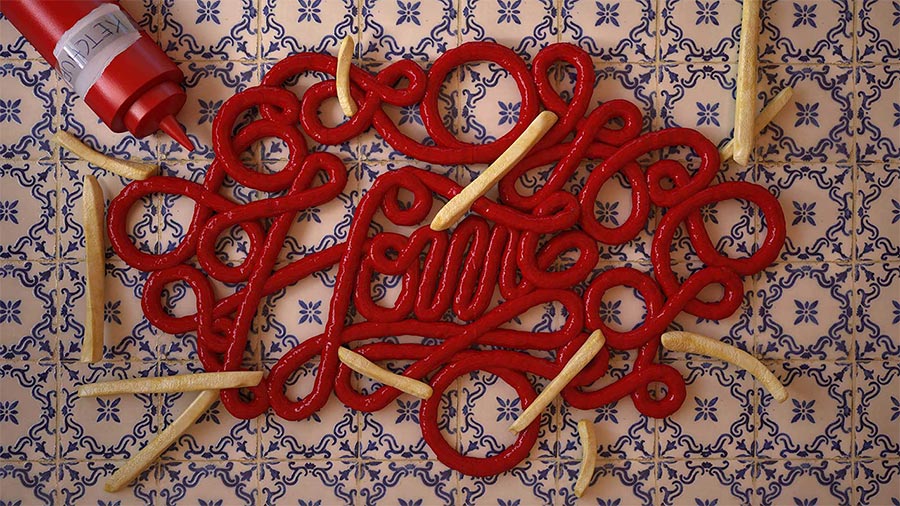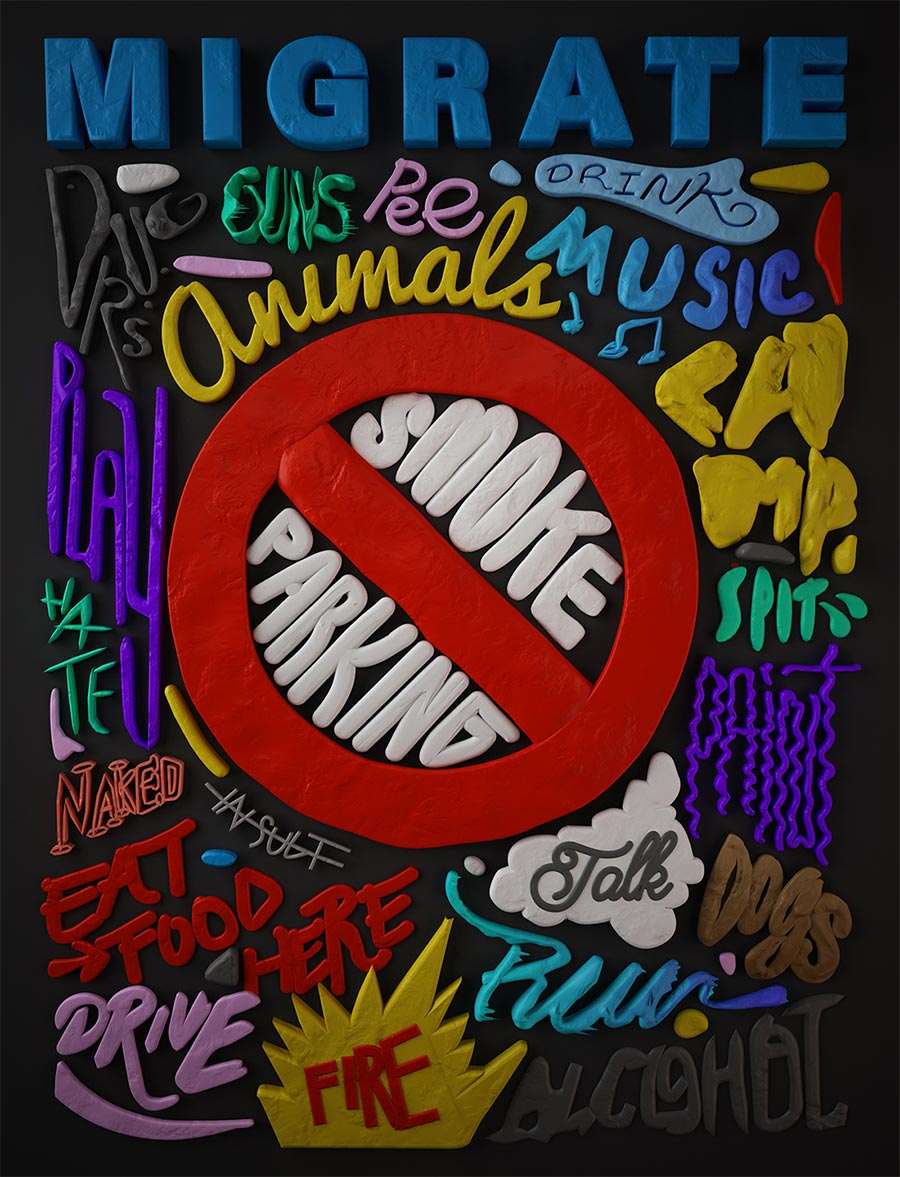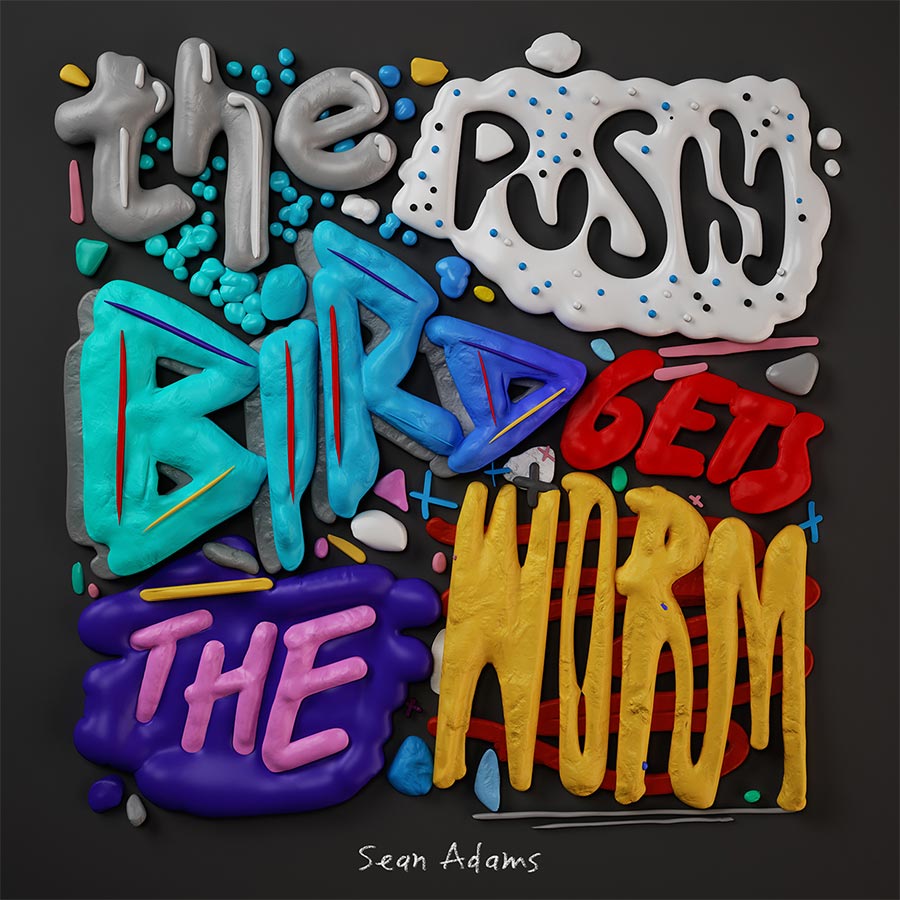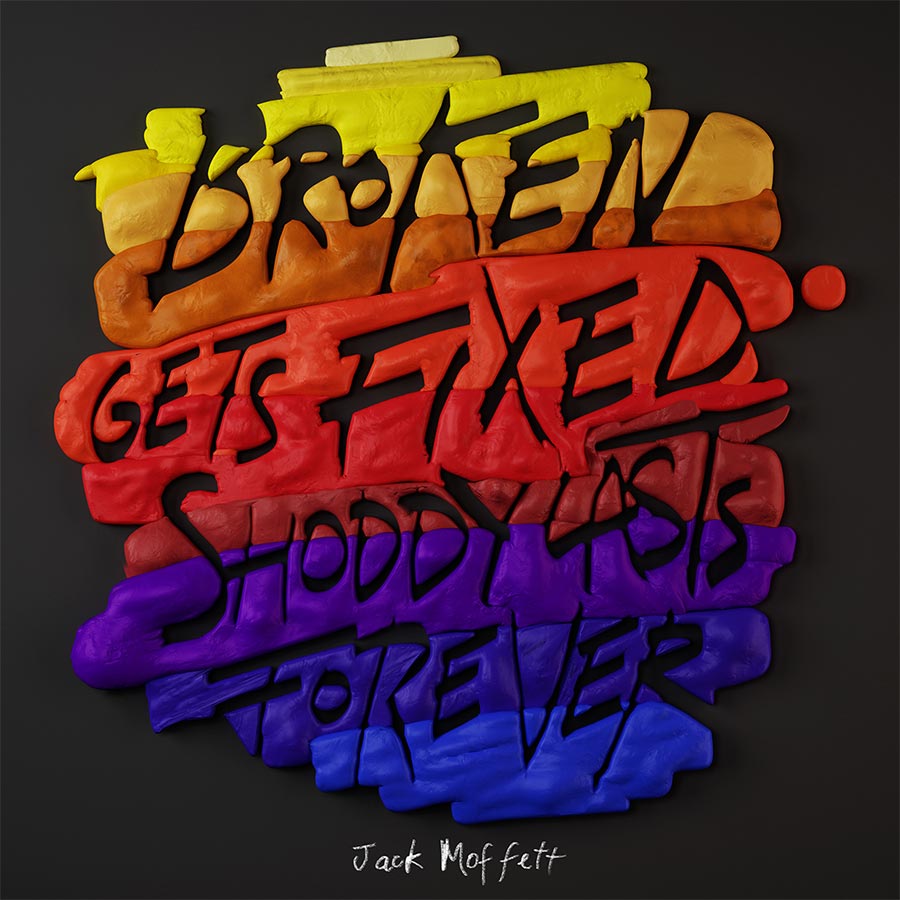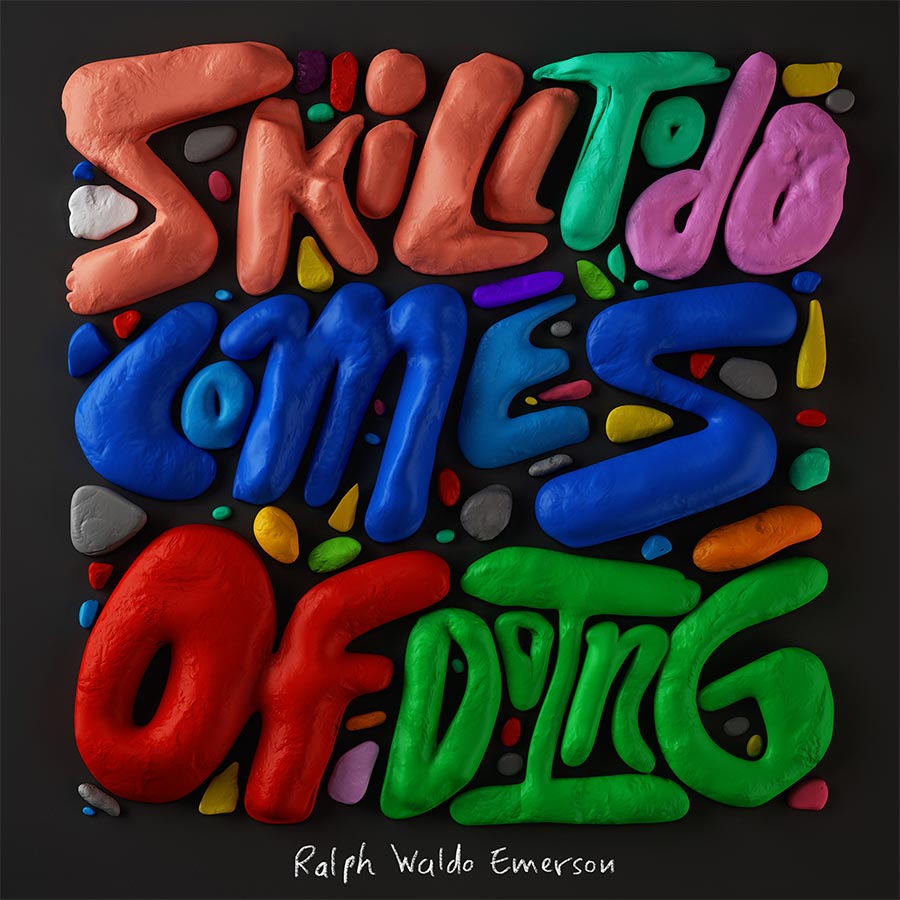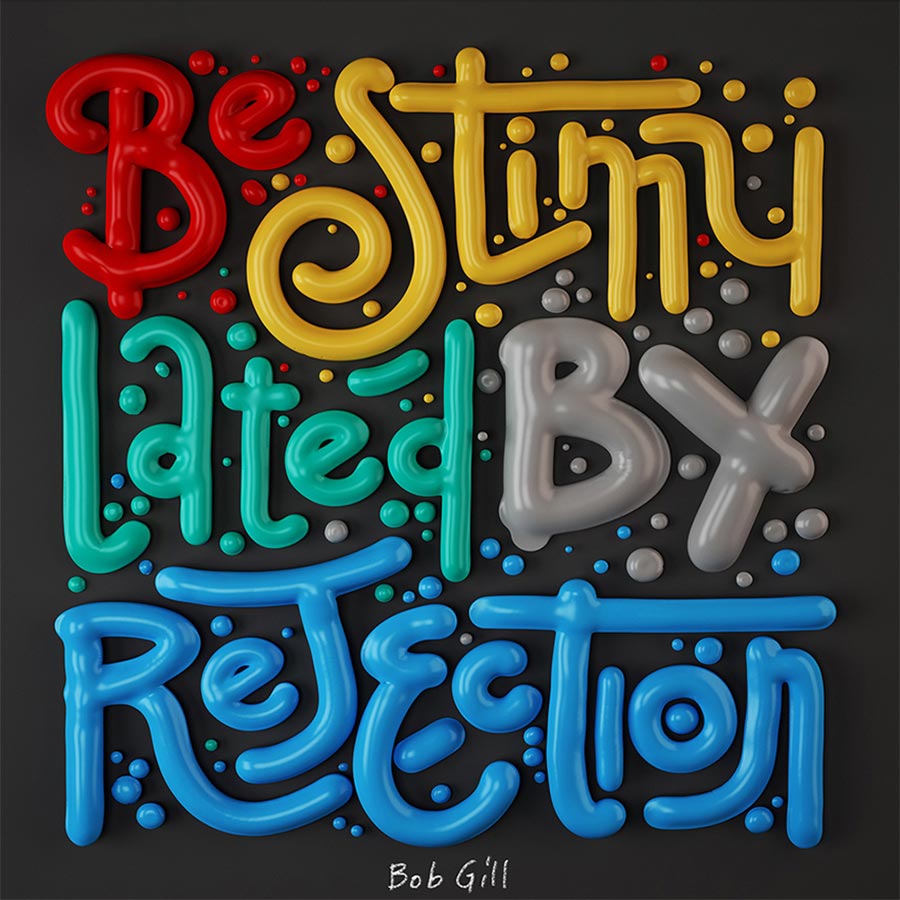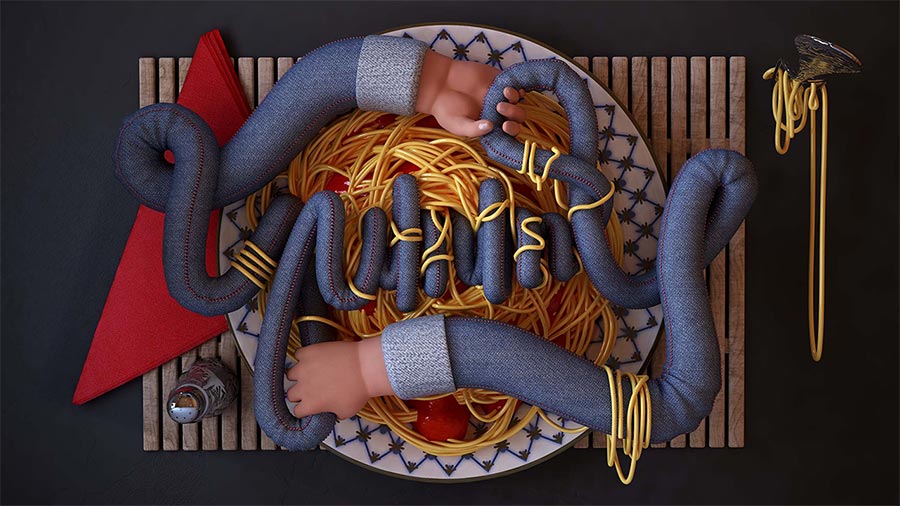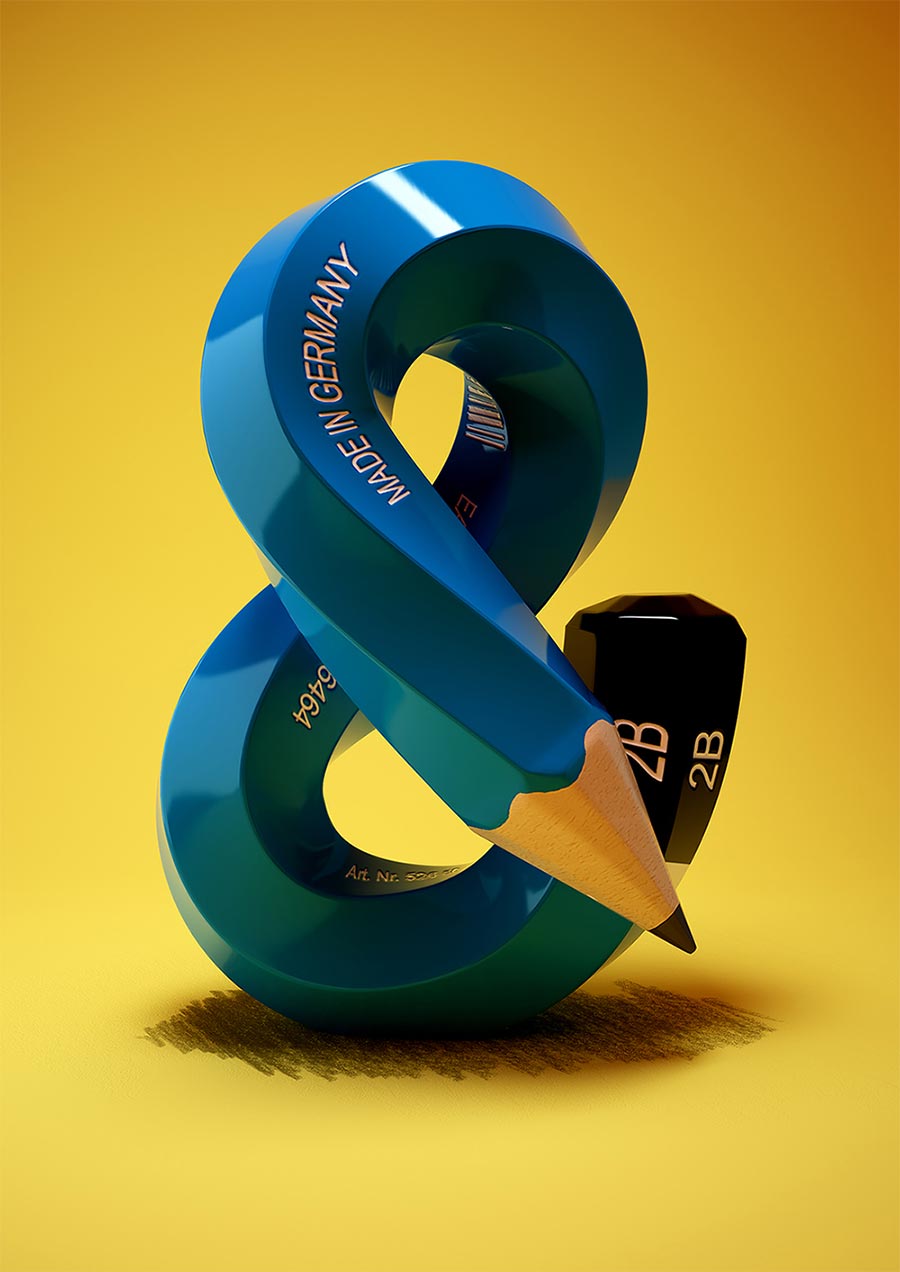
Ausgefallene Buchstaben-Legungen
Typografie: Jenue
Typografie: Jenue Jenue_01
Das Tolle an den Arbeiten des spanischen Art Directors Jenue ist, dass man sich nicht immer sicher sein kann, was nun wirklich aus dem Computer kommt und was real gelegt ist. Immer wieder gibt es Buchstaben-Anordnungen aus Knete und anderen analogen Baustoffen zu sehen, die wunderbar filigran und passend in Szene gesetzt werden. Aber auch die 3D-Animationen und digital-manipulierten Motive sind gelungen. Hier eine kleine Auswahl seiner Arbeiten.
„He is in love with creating words and images, where art and design make a big difference and go further from traditional typography. Always keen to approach new ways to produce beautiful images and forever curious to explore new treatments, combining computer graphics and the real world, Jenue is excited to generate and mix textures and produce compositions, from different elements, as never seen before.“
Typografie: Jenue Jenue_02
Typografie: Jenue Jenue_03
Typografie: Jenue Jenue_04
Typografie: Jenue Jenue_05
Typografie: Jenue Jenue_06
Typografie: Jenue Jenue_07
Typografie: Jenue Jenue_08
Typografie: Jenue Jenue_09